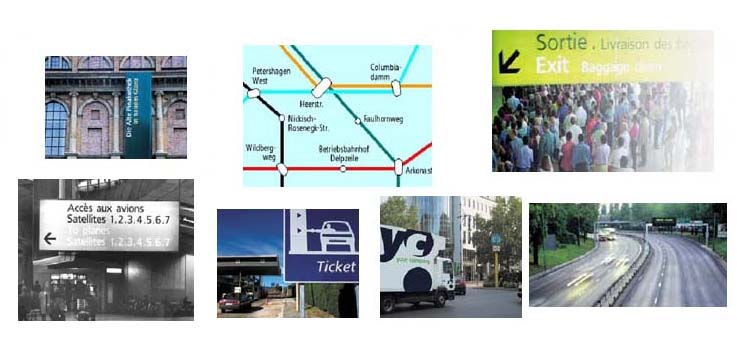
1968年、Adrian Frutiger 氏が新しいパリのシャルル・ド・ゴール空港の標識案内看板や方位用システムなどをもっと発達させる為に依頼されたのが始まり。彼は、モダンなシャルル・ド・ゴール空港の建造物とまさにフィットしたフォント・Frutiger を創りあげた。そう、名字の Frutiger氏そのものが、フォント名となっているのです。
Frutiger フォントは、そんなに装飾的でもないですが、表面的デザイン・個々の文字は、遠くからみても、簡単に認識出来、すごく分かり易いフォントに仕上がってます。その明確さと読みやすさは、標識案内の文字デザイン使用は、勿論ですが、現在では、多方面でも多くの人々に使用できる品質度の高いパーフェクトフォントだと言われてます。現在では、ご存知の通り、Frutiger のフォントは、非常に定評があり、チャートベスト10には、必ずといっていいほど入っている、人気フォントなのです。